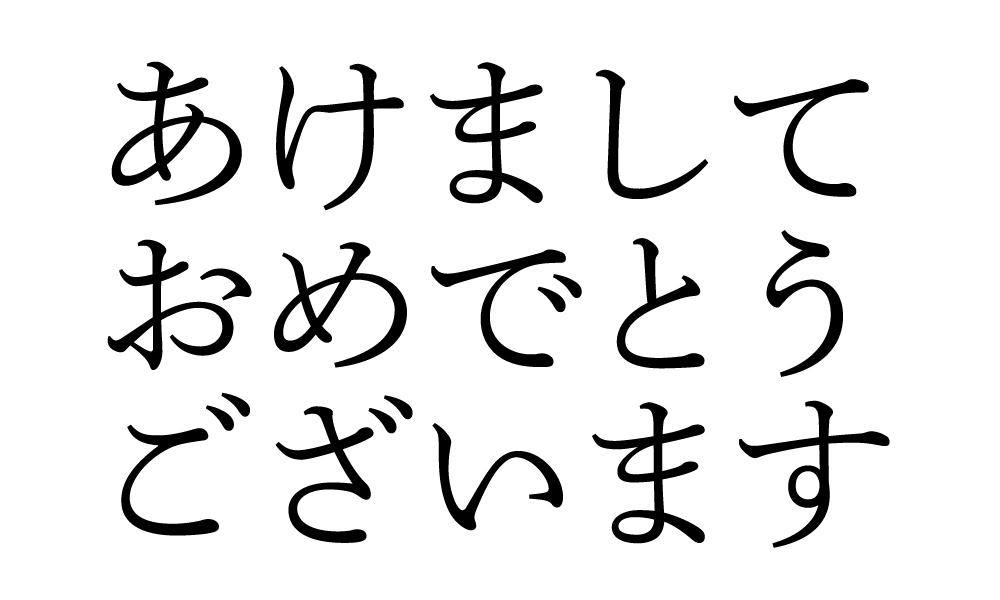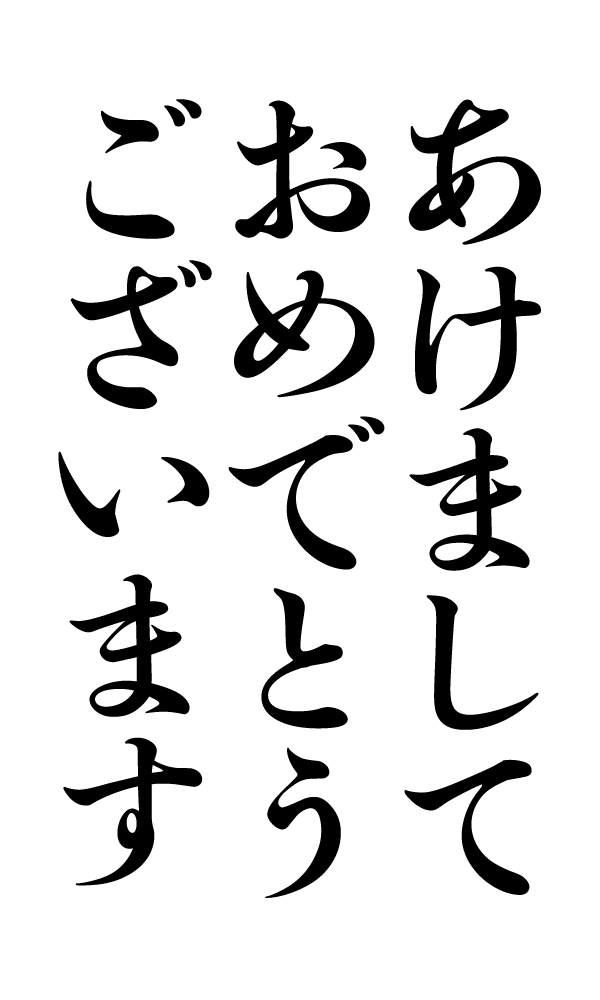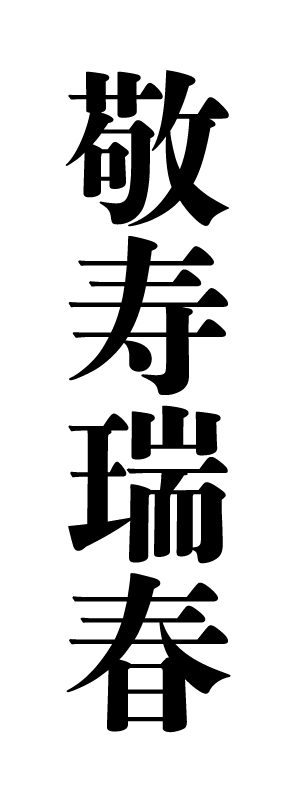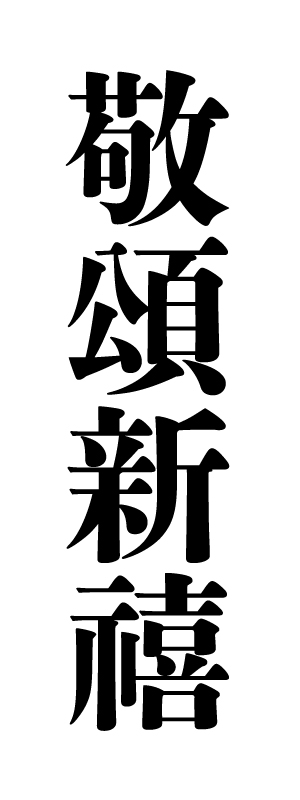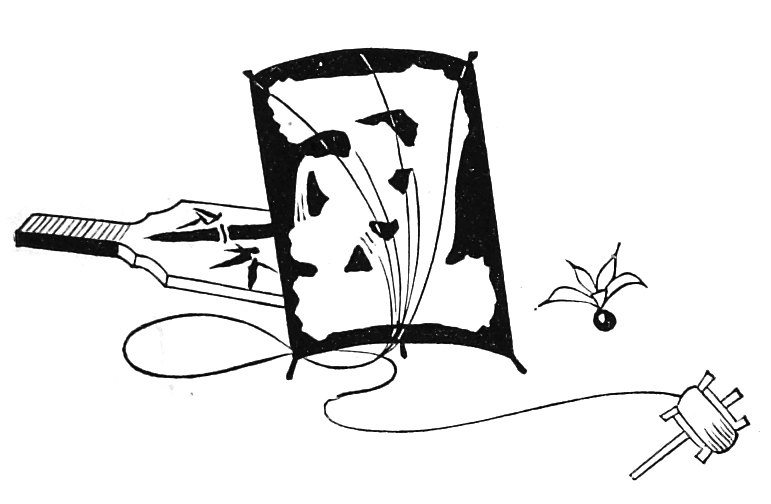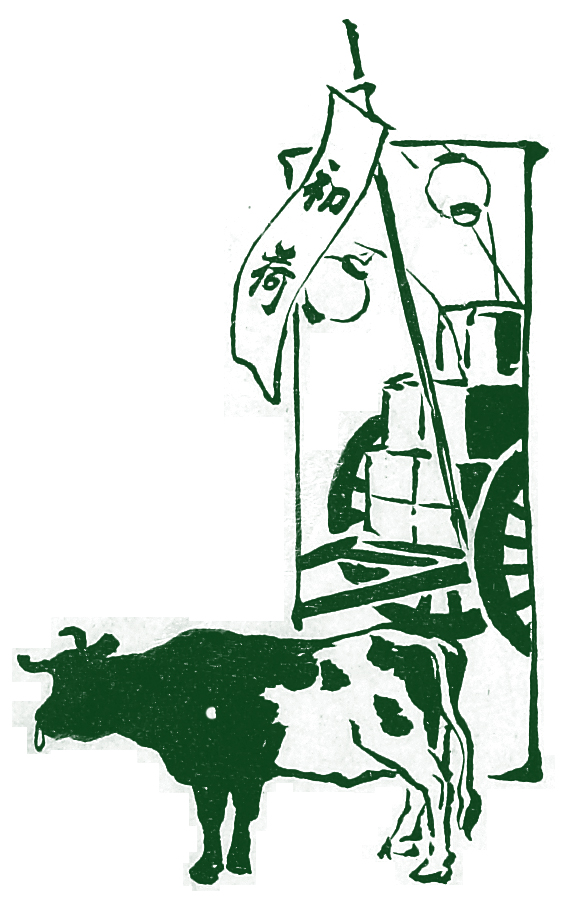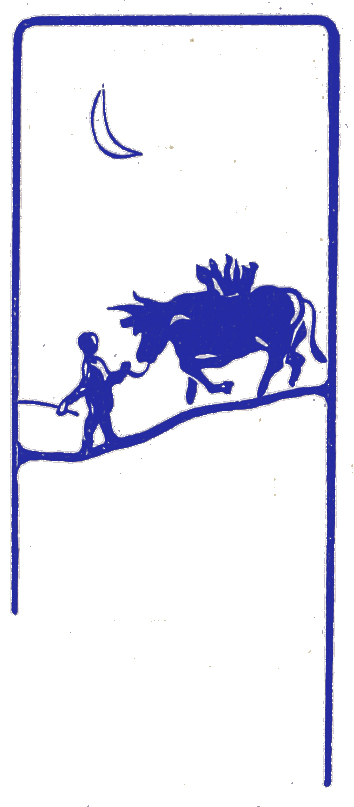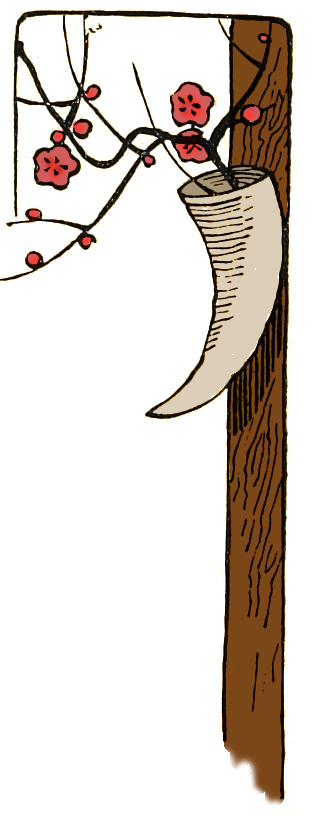
第27回 2008年も大正3年『活版見本帖 Type Specimens』から年賀状を作ろう!
今年こそ年賀状は早めに用意するぞと思いながら例年通りのみなさま、今年も秀英体で年賀状はいかがでしょうか。
今回の秀英体のコネタは、一年間のご愛顧に感謝いたしまして、秀英舎・大日本印刷が誇る最大規模の見本帳、大正3年版『活版見本帖 Type Specimens』から、来年の干支である牛や冬・新春らしい柄などをピックアップいたしました。
まだ年賀状を作っていない方、2005年や2006年、2007年の年賀状コネタと併せ、ぜひご活用ください!
2009の干支、牛集合!
2009年は丑年です。古くから人間の生活に欠かすことのできない牛は、大きな体につぶらな瞳、ゆっくりゆっくり草を食み歩みを進める姿から、忍耐強く困難に立ち向かう生命力を象徴しています。
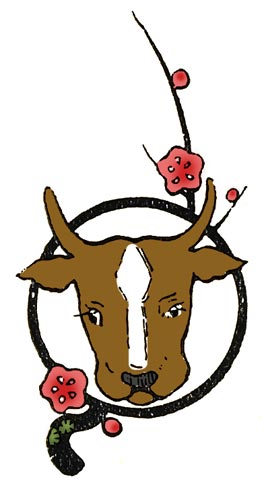
梅と牛。洒落た構図も目を惹きます。牛のまつげが長い!
牛のイラストは、なぜか細長いものがたくさんありました。
ひとことメッセージを添えるのに使いやすいものを選んでみました。
牛が台車を引いて、2009年の正月初荷です。
高張り提灯をずらり並べて、2009年の商売繁盛を願います。
梅の花が飾られていますが、なんと、一輪挿しが牛の角!
牛と梅の組み合わせが多いのはなぜでしょう。
調べてみると、どうも菅原道真公にゆかりのある組み合わせなのだそうです。丑年生まれでさまざまな牛がらみの逸話を残した道真公、一方で梅を愛したことも有名です。道真公を奉る天満宮には、なでると学問に長けるようになるという牛の像と、数多くの梅の木が植えられているところが多いです。
今年の年賀状は、牛だけでなく、ぜひそばに梅の花の絵も添えたいですね。
「あけましておめでとうございます」を秀英体で!
そして絵に添えることばをぜひ秀英体で! 改刻中の秀英体でお正月の言葉を並べてみました。
まずは初号と、昨年はまだ文字が揃っていなかったために登場できなかった中明朝です。初号は去年に比べ、漢字・仮名ともブラッシュアップされています。
細明朝は横組みにしました。しかも、横組み専用仮名です。といっても、秀英細明朝の横組み専用仮名は、形は微妙な修正にとどめて、標準仮名とほとんど同じに見えるのに横組みにしたときに組揺れしないように作りました。
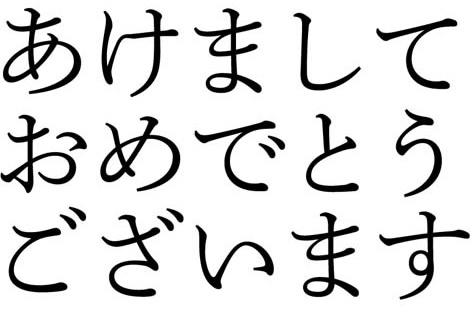
横組み専用仮名も作りましたよ!
年賀状に使われる賀詞を初号でいろいろと組んでみました。ぜひ選んで使ってください。
あっという間の2008年、さまざまなかたちで秀英体をご紹介することができました。
秀英体の使い勝手をさらに向上させるべく、新たな取り組みに着手した年となりました。映像や画面表示、シニア向けに、より文字をはっきり視認できる「秀英横太明朝」を御紹介することができました。また、東京国際ブックフェアでは、明朝体を強力にサポートする相棒・秀英ゴシック体の試作をご来場の皆様にご覧頂く機会に恵まれました。開発チームとしても、扱い慣れた明朝体とは異なり、ゴシック体は試行錯誤が続いていますが、明朝体同様にオーソドックスな使いやすさを追求しながら進めています。
明朝体ファミリーはついに開発もピーク! 2009年こそは、平成の大改刻の成果を皆様にご報告することができるはずです!
来年も、秀英体の取組みをご紹介してまいります。変わらないようで変わっていく秀英体を、2009年もよろしくお願い致します。